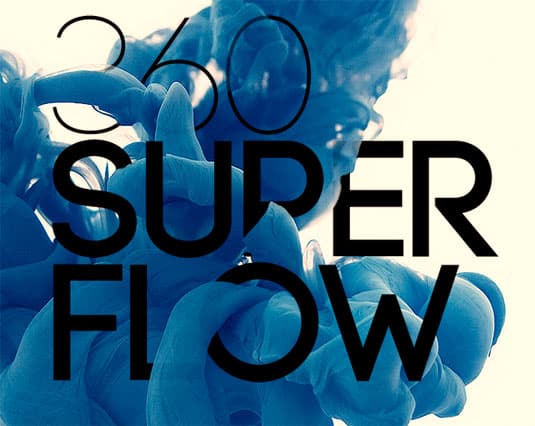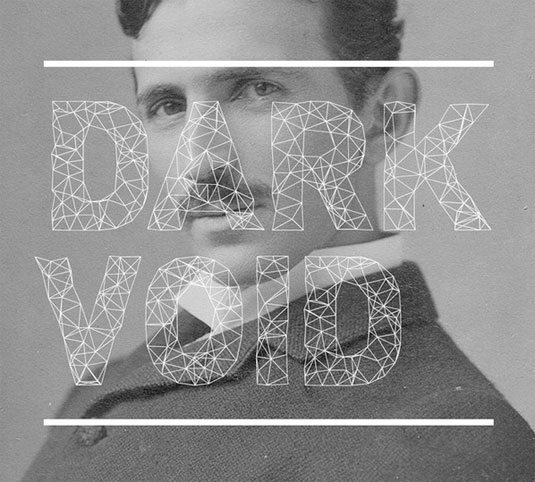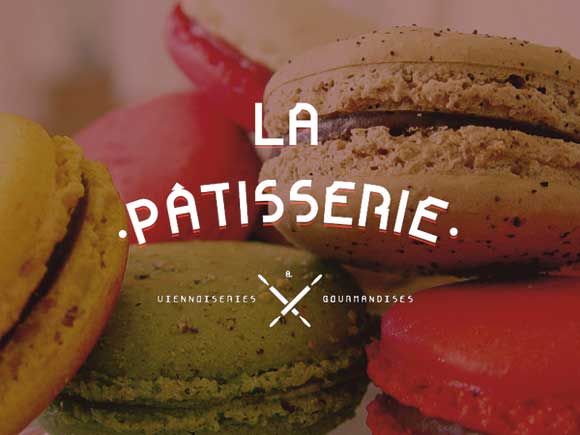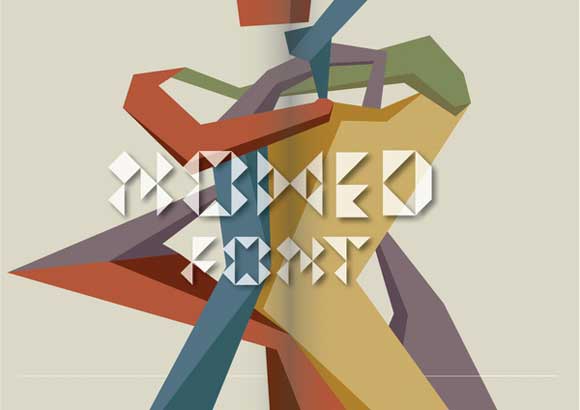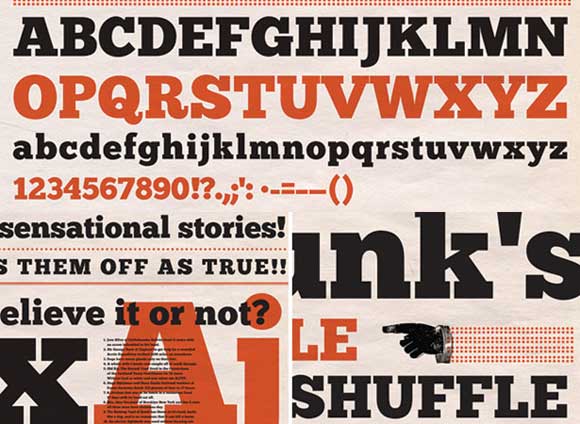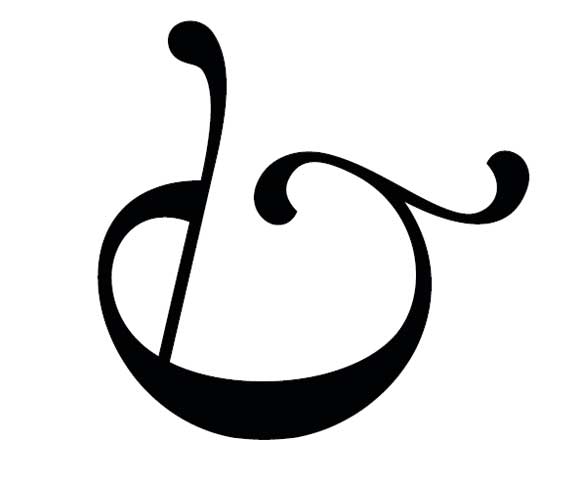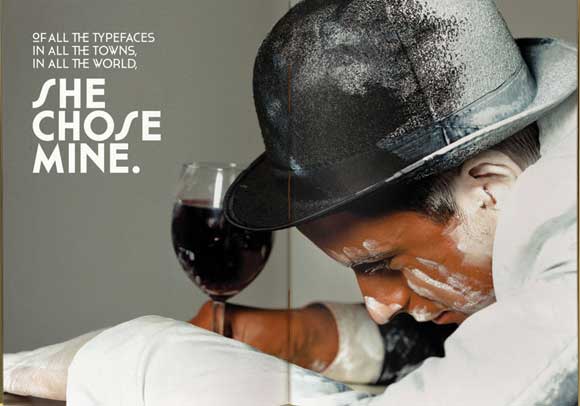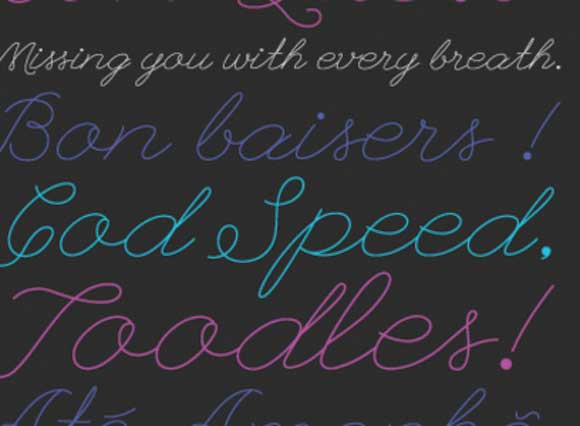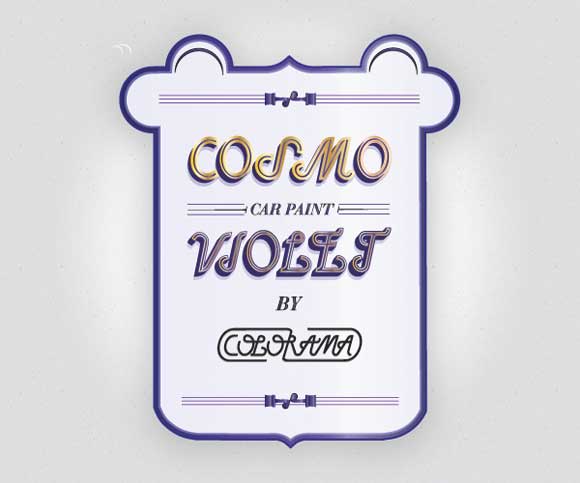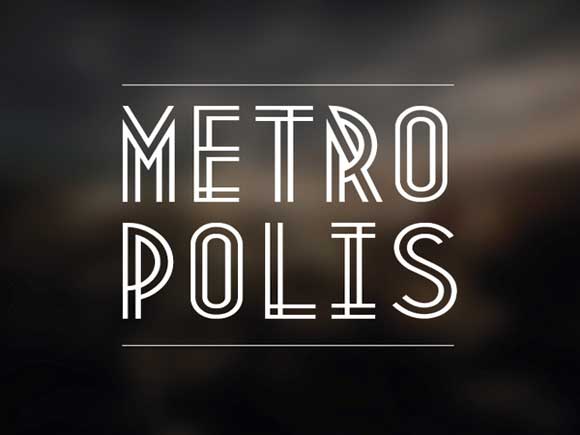
41 font gratutiti per i tuoi progetti web e stampa
Robadagrafici ha sempre ribadito sulle sue pagine facebook che per ottenere un prodotto di qualità e sempre necessario investire una piccola parte del guadagno per migliorare se stessi e i propri prodotti. Tanto vero che non poche sere fa nasceva appunto un discorso su font gratuiti e/o a pagamento. sfatando che la qualità si trova solo se pagi ecco qui 41 font gratuiti (quasi senza limitazioni d’uso)
1. 400ml Type
il font 400ml typeface e stato creato dallo studente Marco Terre. l’obiettivo di Marco era quello di creare un font pulito e leggermente giocoso e si basa sull’idea di combinare dei caratteri provenite dal mondo dei graffiti con i caratteri grafici classici.
Il tipo di carattere è disponibile in quattro stili: normale, grassetto, corsivo e grassetto corsivo regolare. E ‘perfetto per quasi ogni tipo di utilizzo, compreso l’utilizzo per manifesti, web design e illustrazione.
2. Johanna
Johanna è un carattere modulare basato su sei moduli di base e, di conseguenza, vi sono 147 glifi di versatilità in ogni stile. E ‘stato creato da graphic designer spagnolo Adrià Gómez ed è disponibile anche in una versione corsivo.
Amiamo questo retrogusto d‘annata che il font ci trasmette come sensazione, e penso che potrebbe essere utilizzato al meglio nei progetti per il web design. I colori che Adrià ha utilizzato per mostrare il tipo di carattere sono anche un tocco brillante d’artista su come poter giocare e utilizzare al meglio toni di colore e forme.
3. Silverfake
Silverfake è un nuovo moderno font serif gratuito progettato Alexey Frolov, aka MRfrukta. Questo tipo di carattere vintage e funzionale sia per progetti retrò che moderni.
Silverfake contiene solo lettere maiuscole! vi sono inclusi anche alcuni caratteri alternativi . Tornate sul sito di sito Alexey regolarmente, in quanto spesso presenta interessanti set di nuovi font gratuti.
4. Typometry
Questo tipo di font eccentrico è stato realizzato da Emil Kozole per un progetto universitario. Come amante dei “bei colori”, Emil riesce a incorporare in uno stile piuttosto surrealista questo tipo di font su vari progetti, ricordando vagamnte i periodi di sperimentazione tipografica passata . Typometry sarà una grande fonte che vi permetterà di sperimentare cose nuove in una serie di vostri progetti.
Il tipo di carattere è ora una versione Pro in quattro stili e più di 220 caratteri che sono disponibili sia in TFF e formato OTF.
5. Che’s Bone
Questo fonr è stato creato da Filiz Sahin che Dice “Il mio cane ama le ossa. Ho sperimentato con questo tipo di font per il mio cane Che e per altri amanti dei cani. Ha bordi arrotondati e condensati a foma di ossicini.
L’angolo di ogni lettera ha una forma osso che che è la parte preferita di Che. Spero che vi piaccia tanto quanto me!” E ‘gratuito per uso personale e commerciale.
6. Mood Type
sempre da Filiz Sahin un altro font brillante. questo font nasce ispirandosi a una nota azienda svedese di mobili con una forte ispirazione anni 70.
7. Homestead
un altra geniale intutitiva creazione di Lost Type. Inspirrato dal bisogno e ricerca di qualcosa di nuovo homestand vuole esssere il font da richiamare alla memoria una sensazione piacevole comq quella di stare in pantofole a casa propria.
Progettato da Luke Lisi, Homestead è solo in maiuscolo con numeri e segni di punteggiatura.
8. Habana
ispiratio alla capitale Cubana, questo gemoterico font senza grazie, cone le sue curve riporta alla mente la belle epocue cubana ai tempo in cui era famosa per i casino’ i sigari e le belle donne. progettato dalla designer newyorkese Bonnie Clas.
9. CODE Pro
Code Pro e un intera famiglia di font ispirata dai piu famosi Sans Serif come Avant Garde o Futura, ma con un aproccio piu moderno e minimale .
Codefont è applicabile a qualsiasi tipo di grafica web, stampa, grafica in movimento, ecc è perfetto per t-shirt e altre applicazioni come poster e loghi. E ‘disponibile anche in un certo numero di lingue!
by Markie Darkie (a.k.a. Ferdinand Mark Basa.)
40: GRN Burgy
by Marco Goran Romano,
41: Rounded
by Francesco Fonteviva